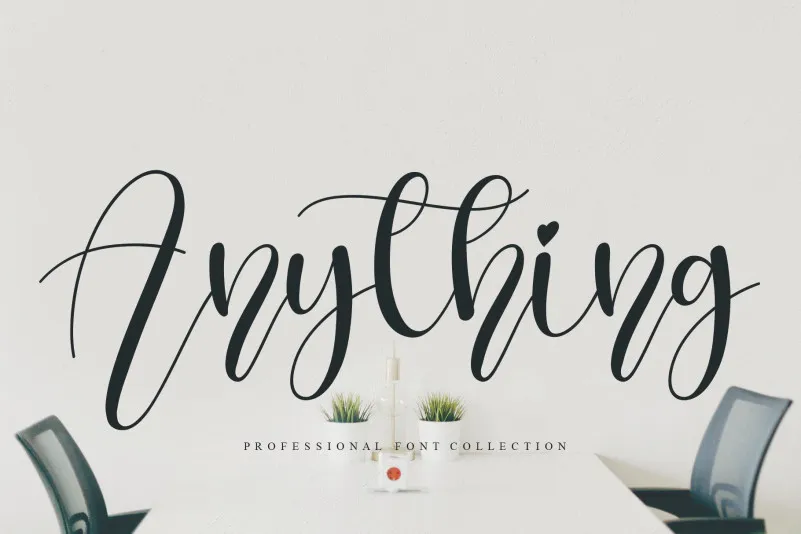
Anything Font – Download Grátis
Essa é uma fonte elegante e divertida, feita a mão com traços suaves e personalizados. Ela oferece um estilo moderno e único, que criará uma atmosfera mágica para seus designs digitais. Este script se destaca pela sua versatilidade, adequando-se perfeitamente tanto aos estilos clássicos quanto às tendências atuais. Para designers amadores ou profissionais, essa fonte será um complemento imprescindível à sua paleta de recursos gráficos. Seja para criar cartazes chamativos ou escrever mensagens inspiradoras, a Anything Font garantirá que seus projetos se destacuem e criem uma conexão verdadeira com o público. Crie agora sua próxima obra-prima digital usando essa fonte moderna, fresca e encantadora.